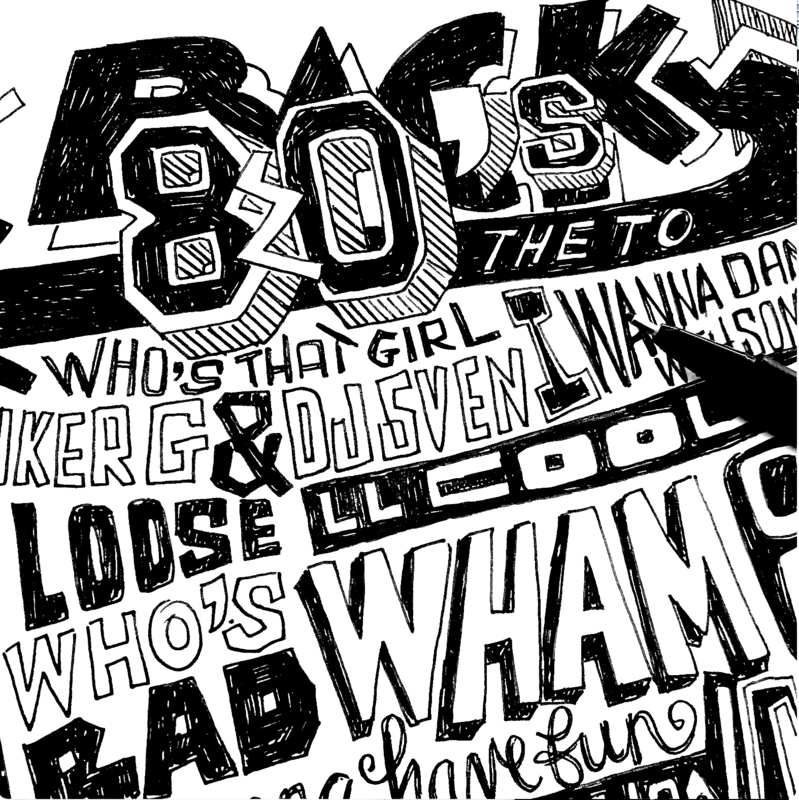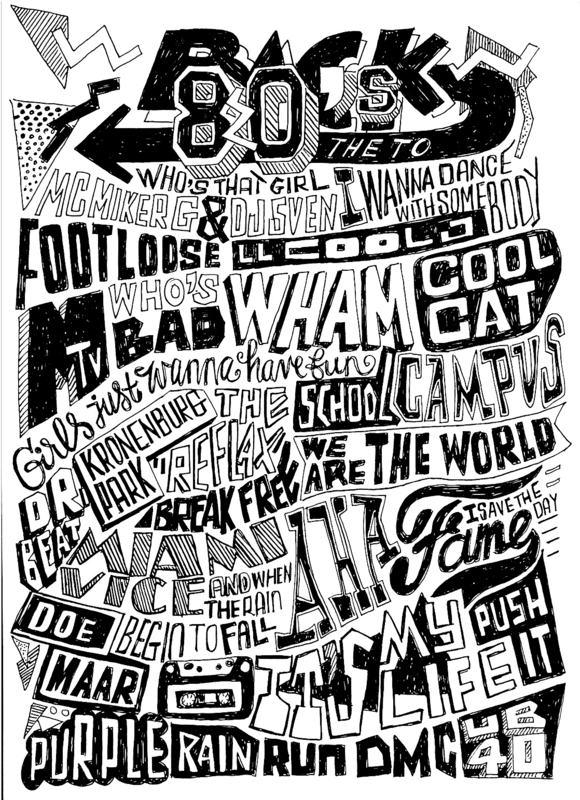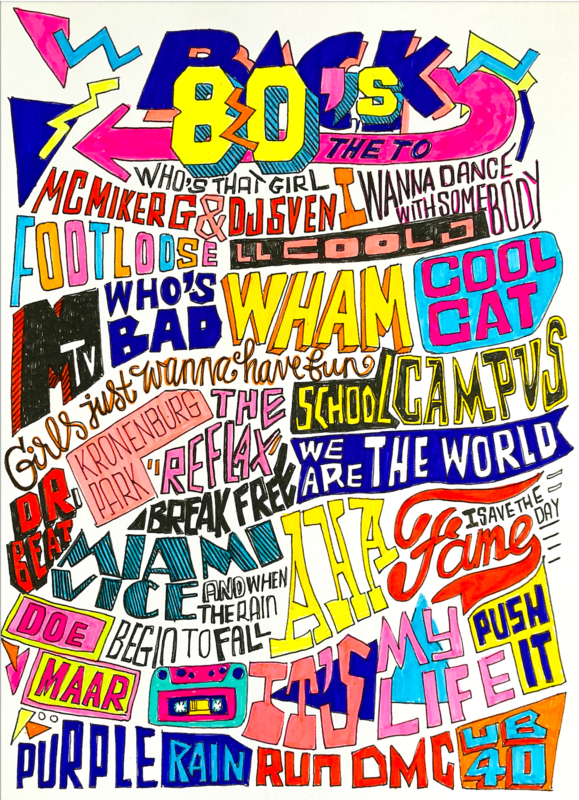
Workshop 'Back to the 80's' | 10 augustus 2024 | 13:30 - 16:00 uur| Voorburg
Maak een nostalgische poster (A4) met liedjes uit de jaren '80.
Jaaaa, we gaan deze middag even terug naar de jaren '80. Ik laat je zien hoe de vormgeving er toen uitzag: veel vormen, veel felle kleuren en vooral neonkleuren. Een wilde tijd waarin letters op zoveel verschillene manieren werden gebruikt. Een combinatie van veel invloeden die samen kwamen. Om nu te zeggen was het mooie tijd qua vormgeving? Niet echt, maar wel een hele spannende tijd. We maken een header van de poster in jaren '80 stijl, ik leg je uit hoe je dat kunt doen. Daarna gaat de playlist aan met jaren '80 liedjes en gaan we gewoon beginnen. Uiteraard leg ik tussendoor -terwijl je bezig bent- iets uit over letters zodat je dat meteen kunt toepassen. We gaan direct beginnen, geen schetsen vooraf. Je mag zelf kiezen of je in zwart wit wilt werken of in kleur. Aan het einde van de workshop heb je jouw eigen jaren '80 poster gemaakt vol met herinneringen!